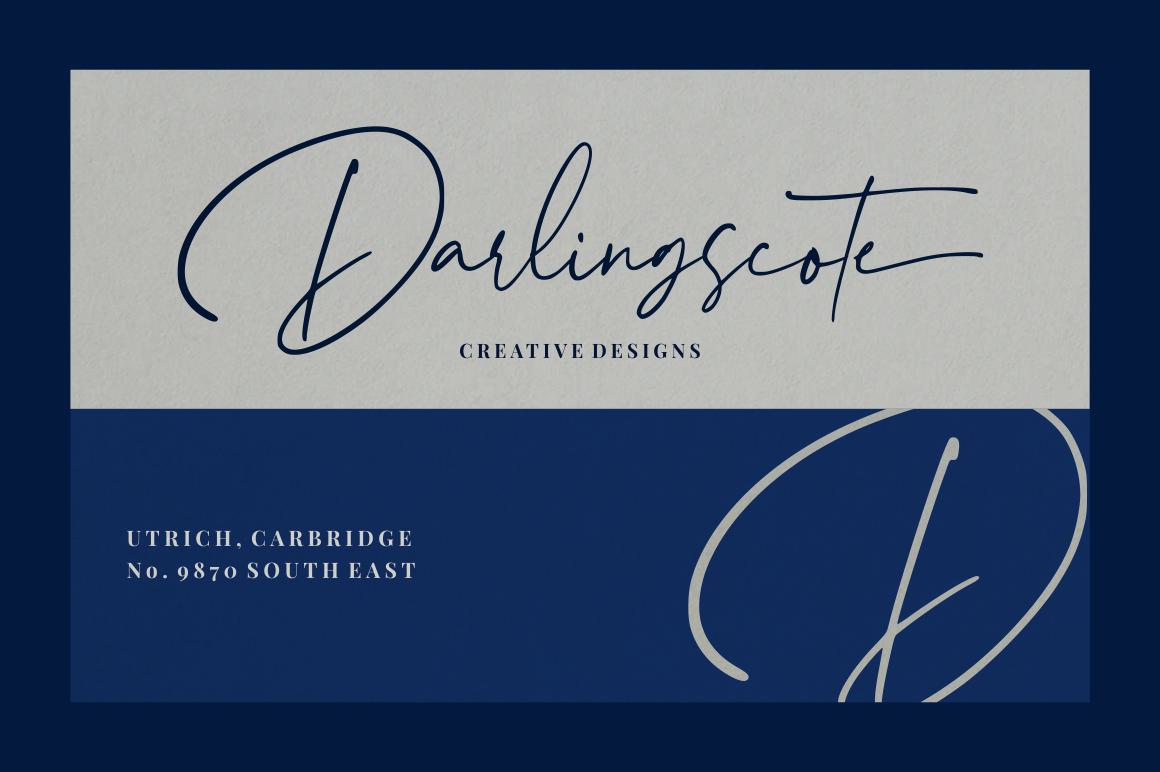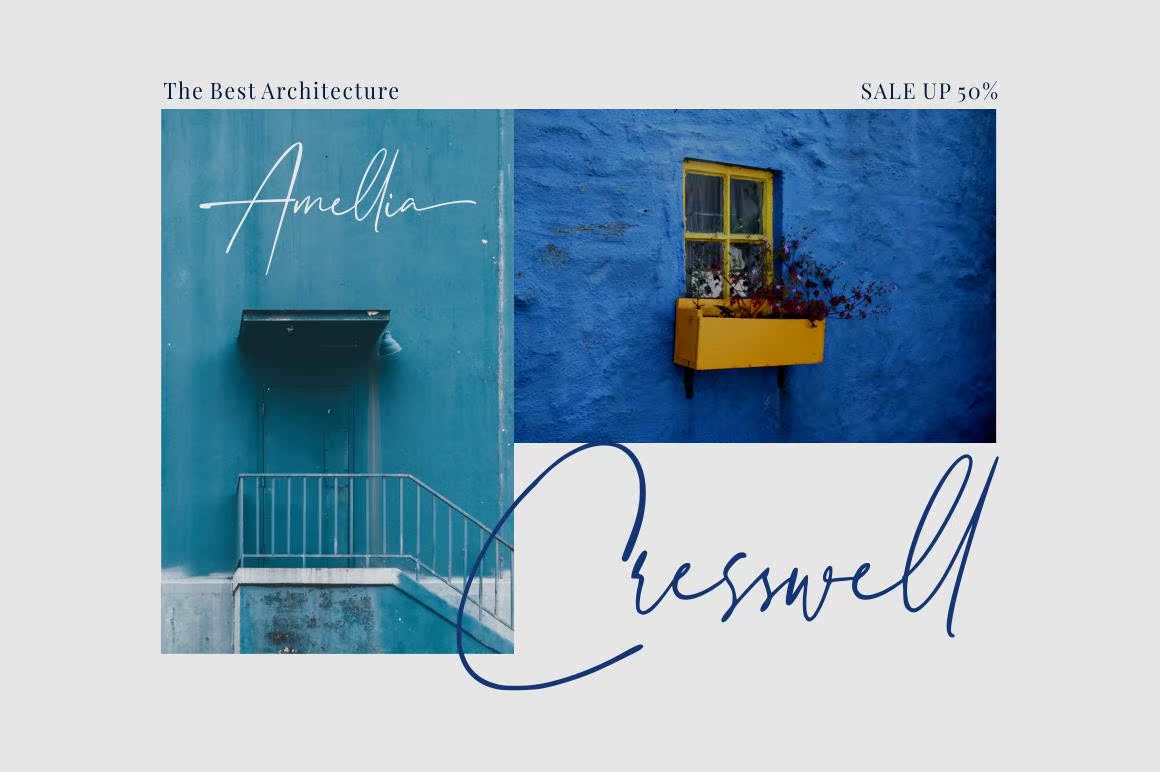
汉普郡–针对自然与现代的随意签名和书写字体。我非常擅长于标识、邀请、文具、婚礼设计、社交媒体、广告、产品包装、产品设计、标签、摄影、水印、特殊物品等。此字体包括:汉普郡OTF-TTF-WOFF、连字、,还有多种语言支持。汉普郡–针对自然和现代字体的随意签名和书写字体。我非常擅长于徽标、邀请、文具、婚礼设计、社交媒体、广告、产品包装、产品设计、标签、摄影、水印、特殊品等。这种字体包括:汉普郡OTF-TTF-WOFF、连字和多种语言支持。